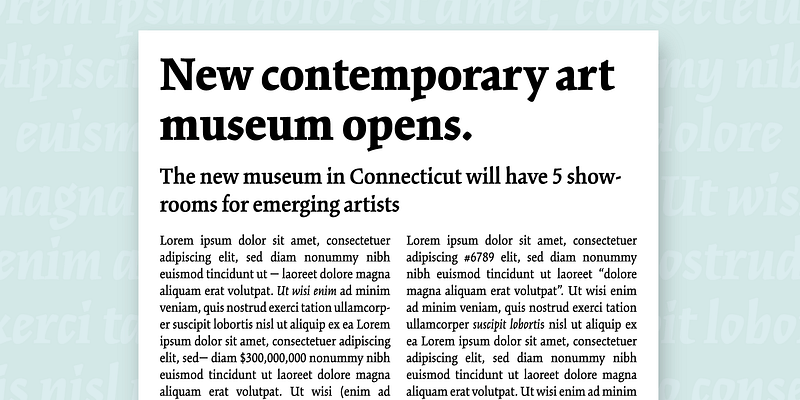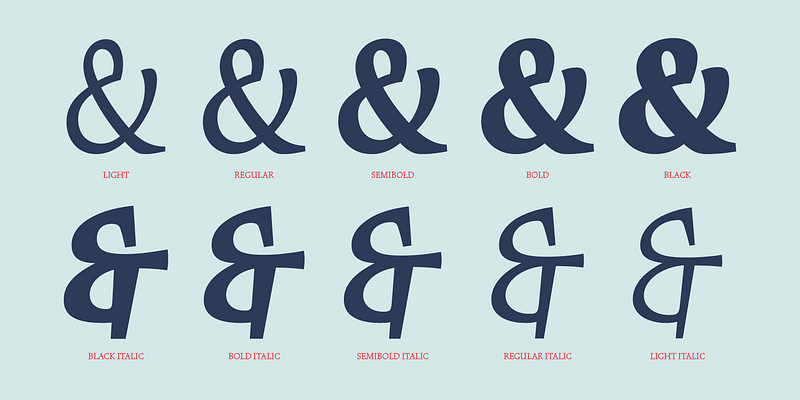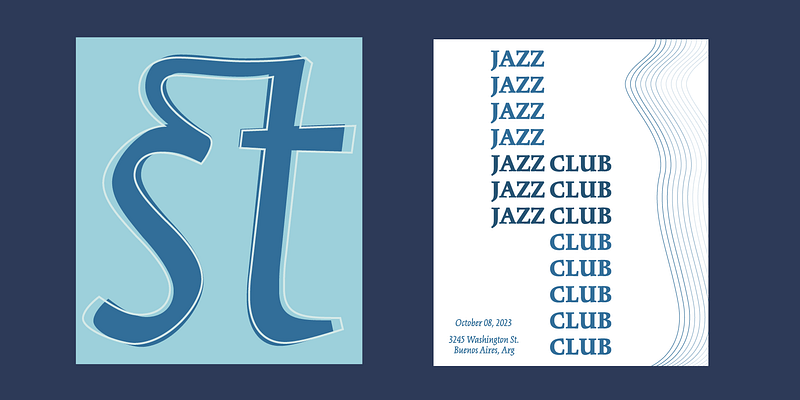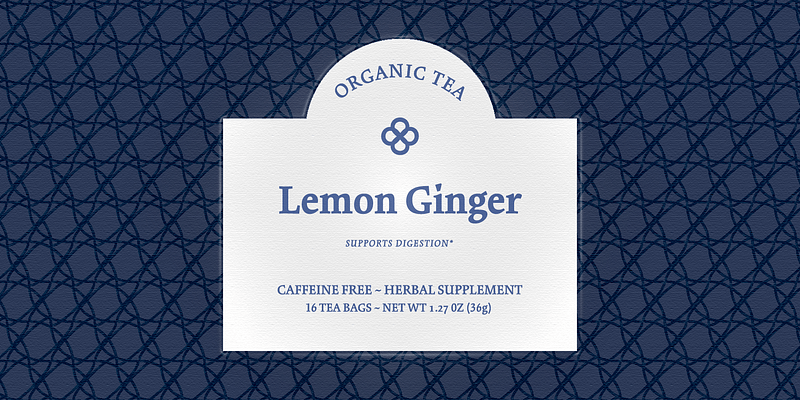
Kinesis est une famille de polices unique et pleine de vie conçue par Mark Jamra. Le mouvement propre à cette conception est aussi bien adapté à l’affichage qu’aux blocs de texte énergiques. Cette police offre un équilibre entre formes non conventionnelles et calligraphie expressive, avec toutes les caractéristiques d’une police de texte lisible.